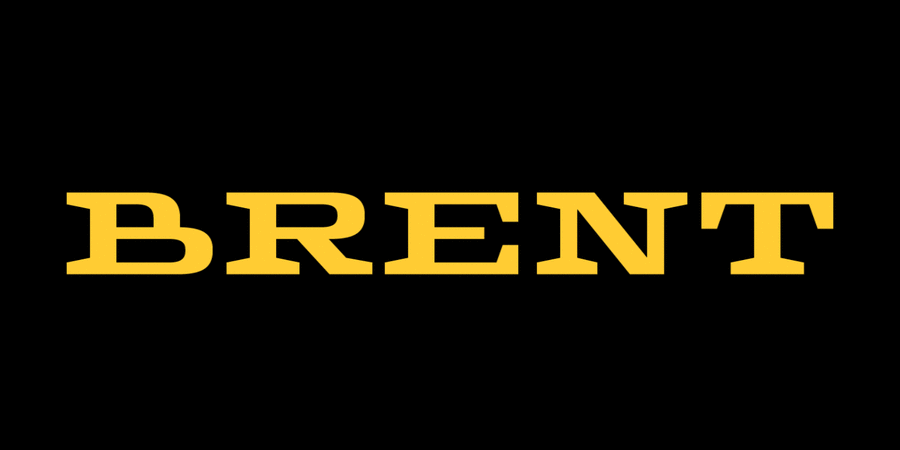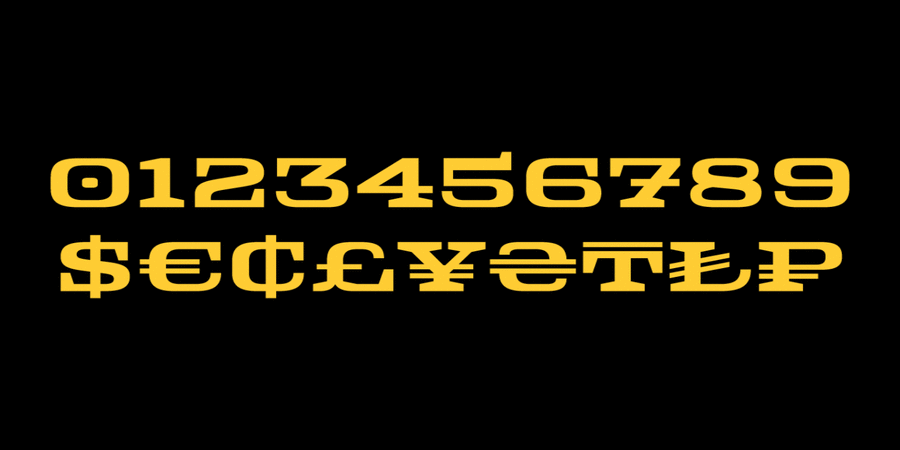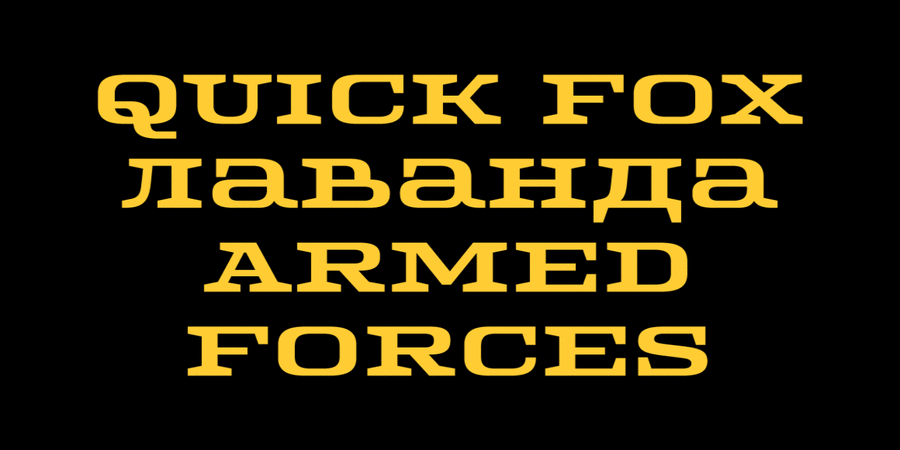
Brent 4F - широкий брусковый шрифт для вывесок, упаковки и логотипов в духе 50-х. Подойдет для всего, в чем важна надежность, высокое качество и традиции. Шрифт разработан Сергеем Ткаченко в 2013 году.
Особливості сімейства шрифтів Brent 4FХіт десятиліття:
Асоціації з сімейством шрифтів Brent 4FОсобистість і характер гарнітури:
гучний, просторий, ремісничий, мачо, ностальгічний, консервативний, дорогий, сильний, оригінальний, виразний, характерний, пафосний, амбітний, авторитетний, владний, впевнений, багатий, традиційний, переконливий, значний, серйозний, обов'язковий, солідний, стабільний, якісний, добротний, чіткий, цінний, самостійний, відповідальний, західний, статичний, важкий, квадратний, яскравий, помітний, мотивуючий, блатний, стійкий, вінтажний, рівний, твердий, різкий, претензійний, олдскульний, залізний, міцний, надійний, крафтовий, бандитський, сексуальний
кузня, ремесло, джинси, стайня, кінь, револьвер, гамбургер, гроші, банк, монета, алкоголь, тютюн, віскі, фінанси, суд, влада, ломбард, сейф, правосуддя, м'ясо, економіка, карти, гра, сигари, обід, вечеря, магазин, торгівля, детектив, мафія, одяг, взуття, ресторан, бар, вантажівка, далекобійник, інструмент, техніка, сировина, нафта, паливо, автомобіль, верстат, казино, Трофей, нагорода Гарнітура має ознаки стилів: